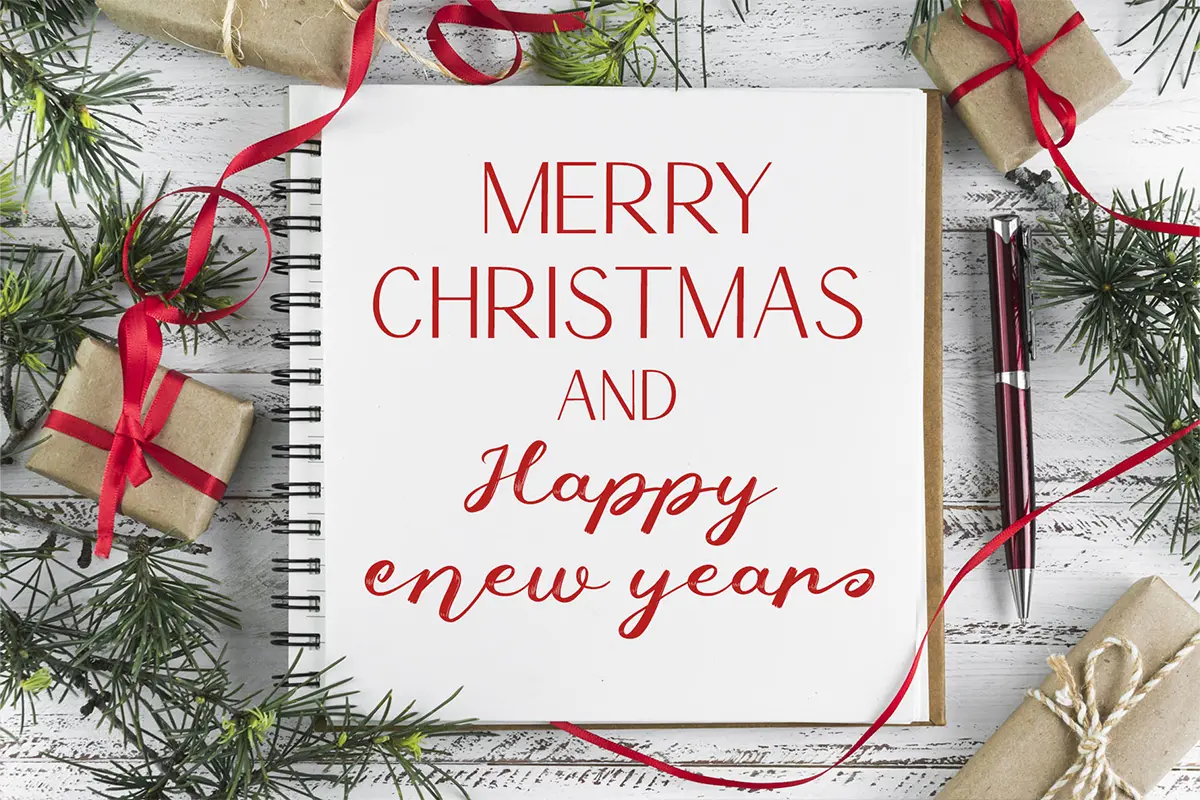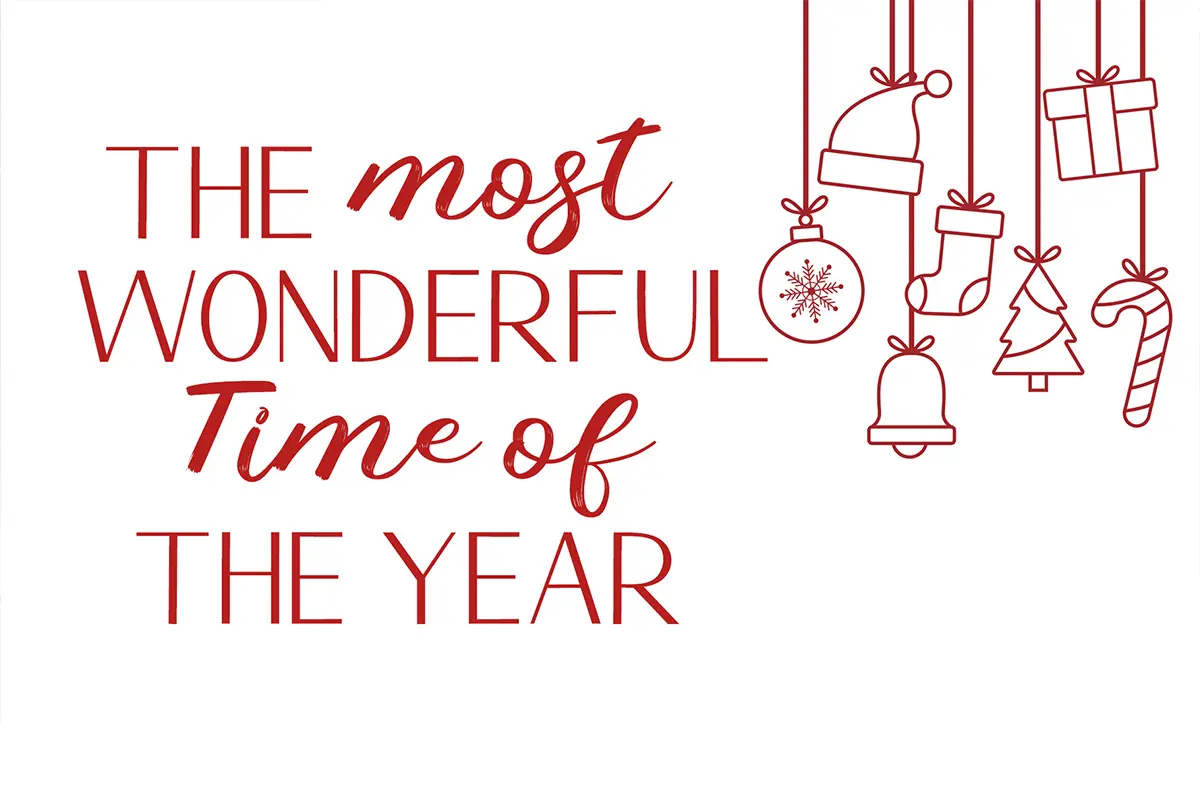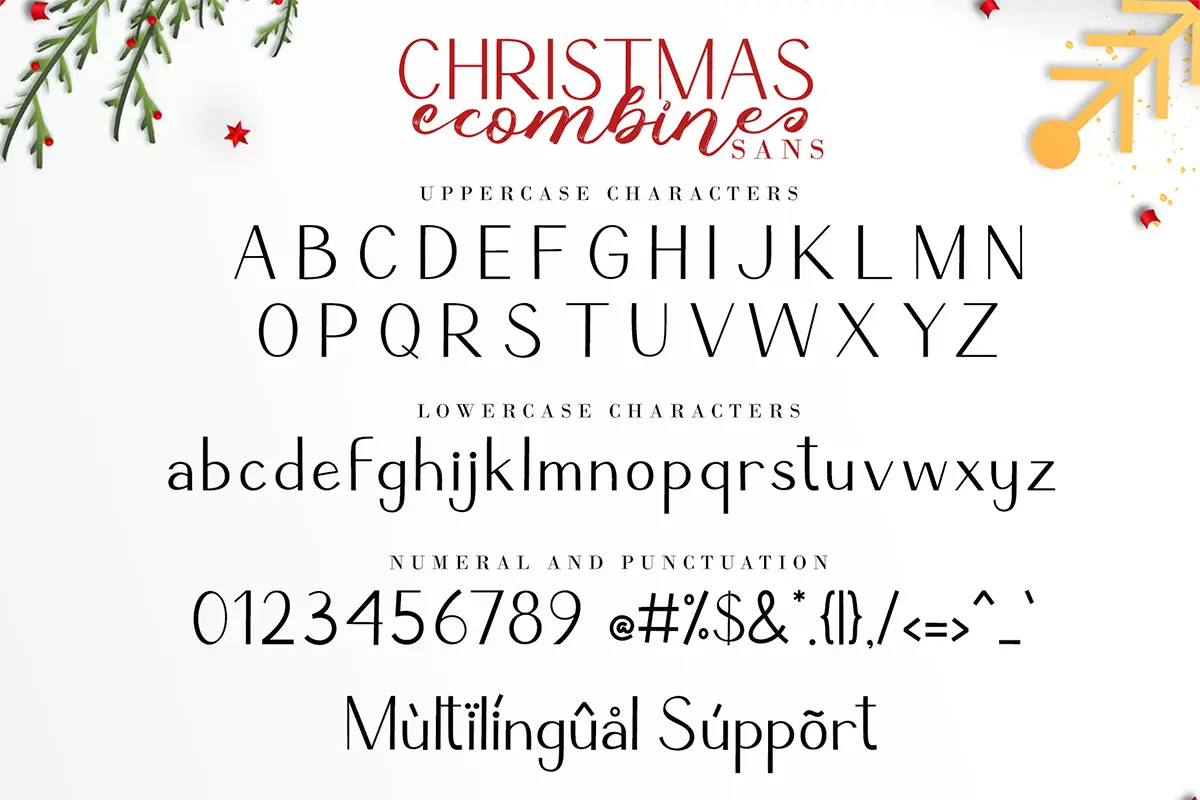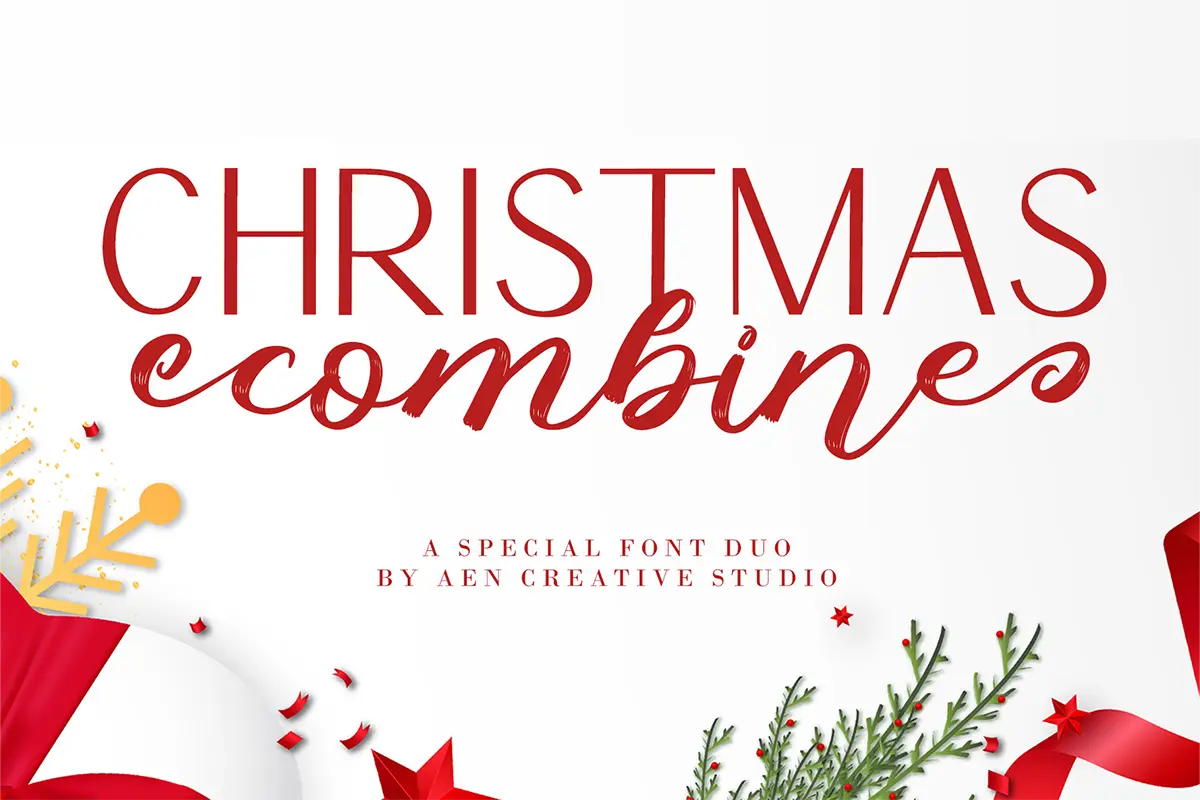
فونت کریسمس دستنویس
فونت Christmas Combine شامل دو فونت هماهنگ و مکمل هست که میتونه به طراحیهای شما حالوهوای شیک و شاد کریسمسی بده. این فونتها چه بهصورت جداگانه و چه در کنار هم استفاده بشن، برای پروژههای خلاقانه و تزئینی عالی هستن. همچنین این مجموعه PUA Encoded هست، یعنی بهراحتی میتونی به تمام گلیفها و سوئشها دسترسی داشته باشی.
⭐ ویژگیهای محصول
- شامل دو فونت مکمل و هماهنگ
- مناسب برای طراحیهای کریسمسی و تزئینی
- PUA Encoded برای دسترسی آسان به گلیفها و سوئشها
- ایدهآل برای پروژههای چاپی و دیجیتال
🎯 موارد استفاده
- طراحی کارتهای تبریک کریسمس
- ساخت پوسترها و فلایرهای جشن و مناسبتها
- تزئین محصولات چاپی مثل لیبل، بستهبندی و تیشرت
- استفاده در پروژههای دیجیتال و محتوای شبکههای اجتماعی